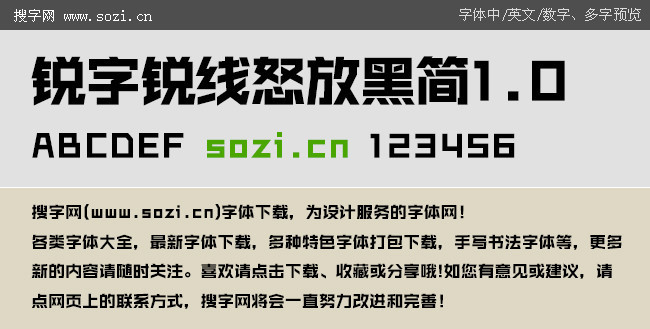
銳字銳線怒放黑簡(jiǎn)1.0
搜字網(wǎng)提供一款非常藝術(shù)的銳字銳線怒放黑簡(jiǎn)1.0下載,銳字銳線怒放黑簡(jiǎn)是一款銳字工房出品的藝術(shù)字體,該字體極具藝術(shù)感,簡(jiǎn)潔大方,適用于包裝印刷、廣告設(shè)計(jì)、平面設(shè)計(jì)、書籍報(bào)紙等領(lǐng)域。